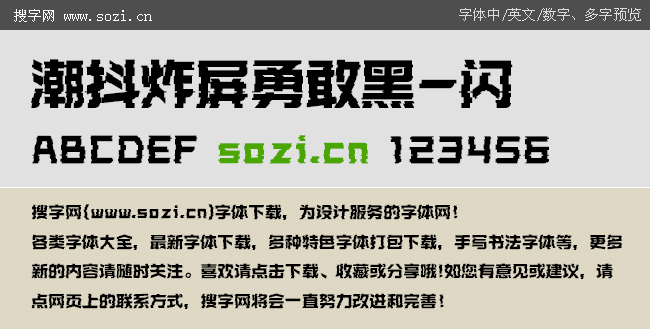
潮抖炸屏勇敢黑-閃
搜字網(wǎng)提供一款潮抖炸屏勇敢黑-閃中文字體下載,潮抖炸屏勇敢黑-閃是一款藝術(shù)黑體字體,潮抖炸屏勇敢黑以黑體字為基準(zhǔn),加入抖動(dòng)筆畫(huà)與切割錯(cuò)位效果,潮流動(dòng)感,重新定義時(shí)尚字體。適合用于標(biāo)題設(shè)計(jì)、海報(bào)設(shè)計(jì)、包裝設(shè)計(jì)等場(chǎng)景廣泛應(yīng)用。(本字體為個(gè)人非商用版,商用請(qǐng)聯(lián)系作者購(gòu)買(mǎi)授權(quán)。官方網(wǎng)址:http://www.reeji.com 聯(lián)系方式:021-58597892)
- 風(fēng)格類(lèi)別: 現(xiàn)代藝術(shù)體